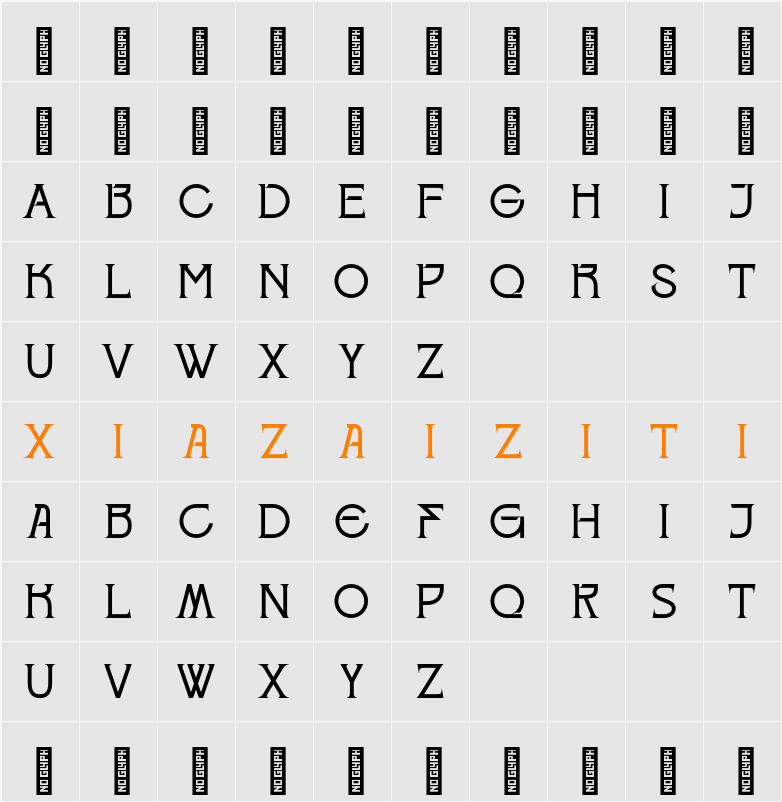
Freva - Demo Version
Freva - Demo Version,这款字体结构工整、笔画清晰,兼顾美观与易读性,适用于标题、正文、海报、包装、LOGO 等多种场景。字形优雅稳定,风格百搭耐看,适配日常排版与创意设计,让文字呈现更舒适、更具质感。Freva - Demo Version一笔一画,皆是细节,以均衡的比例、流畅的线条打造舒适视觉体验,字形端正大气,风格简约现代。无论是商业设计、品牌宣传还是日常排版,都能轻松驾驭,让文字更有格调与力量。Freva - Demo Version字体下载。
• 设计师: Sigit Dwipa Raharjo